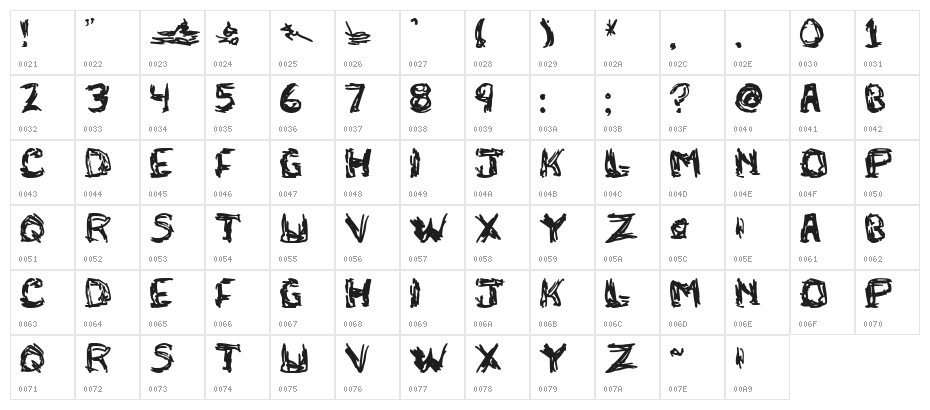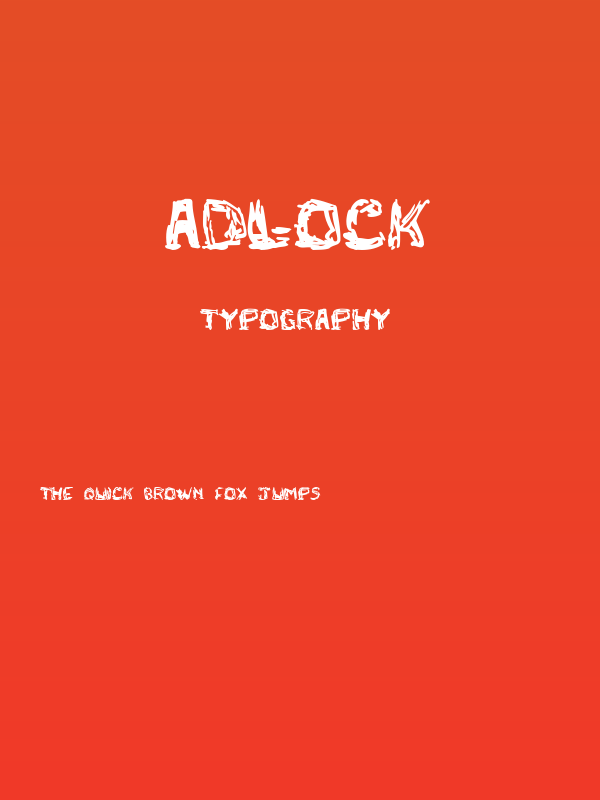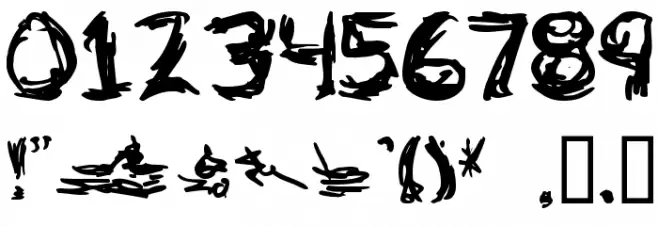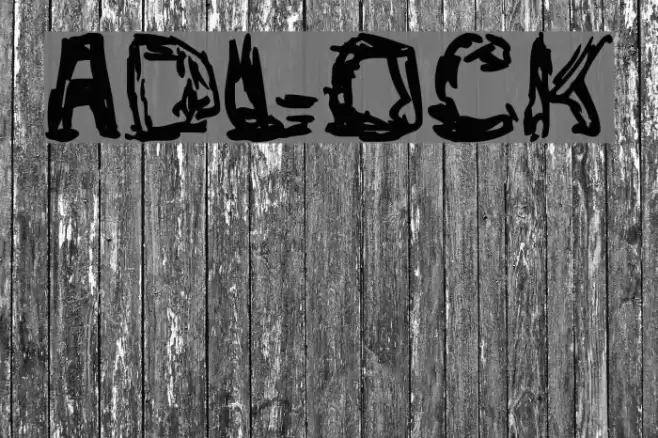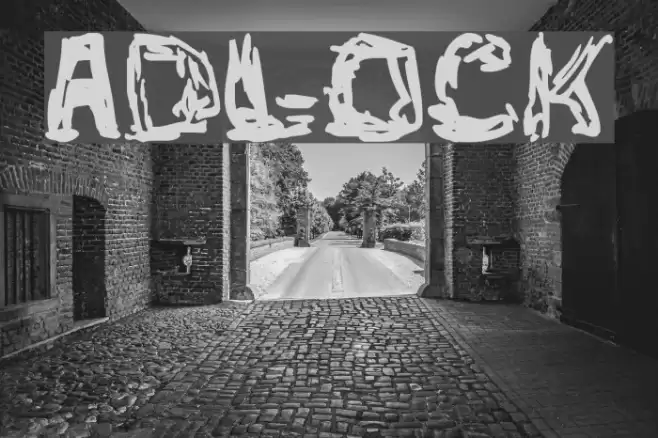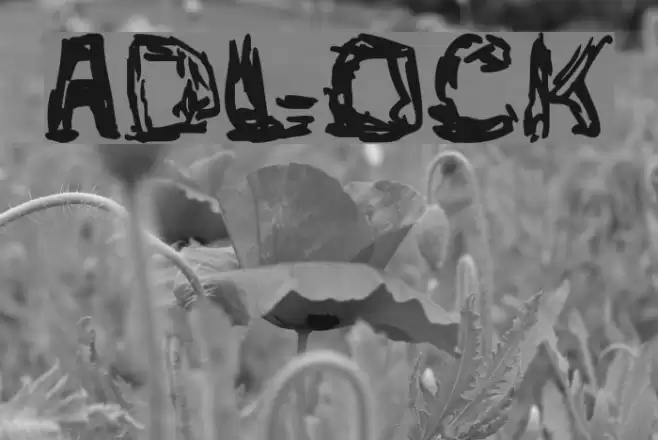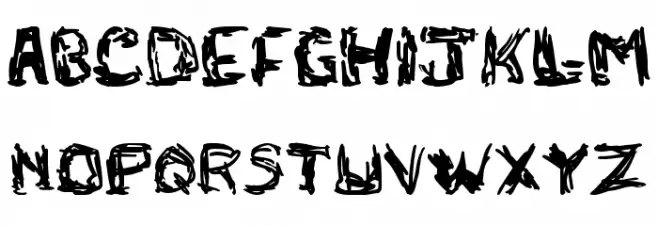
adlock Font
| Proiecte propuse | Ideal for street art-inspired designs, edgy posters, album covers, or any project seeking a rebellious and artistic touch. |